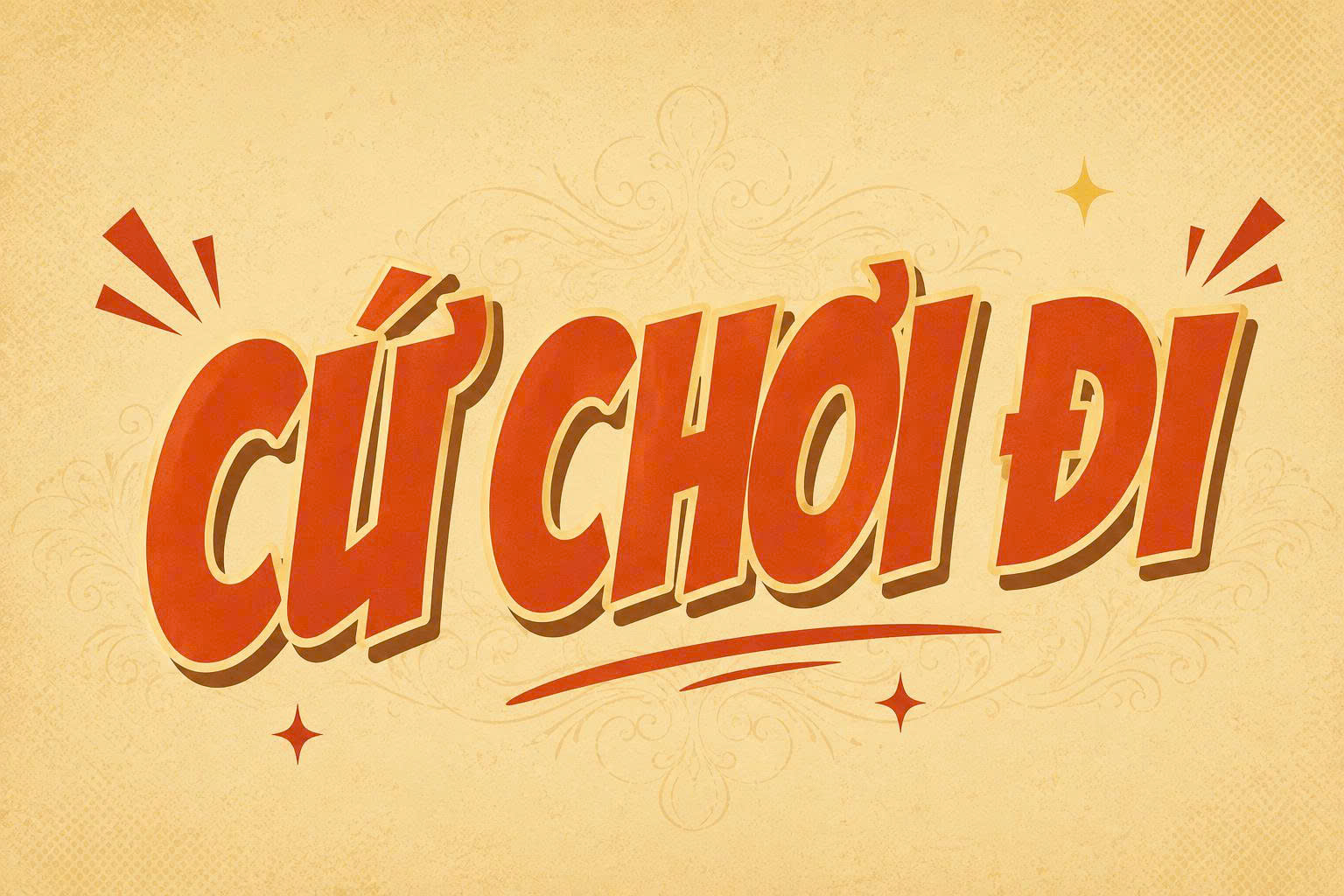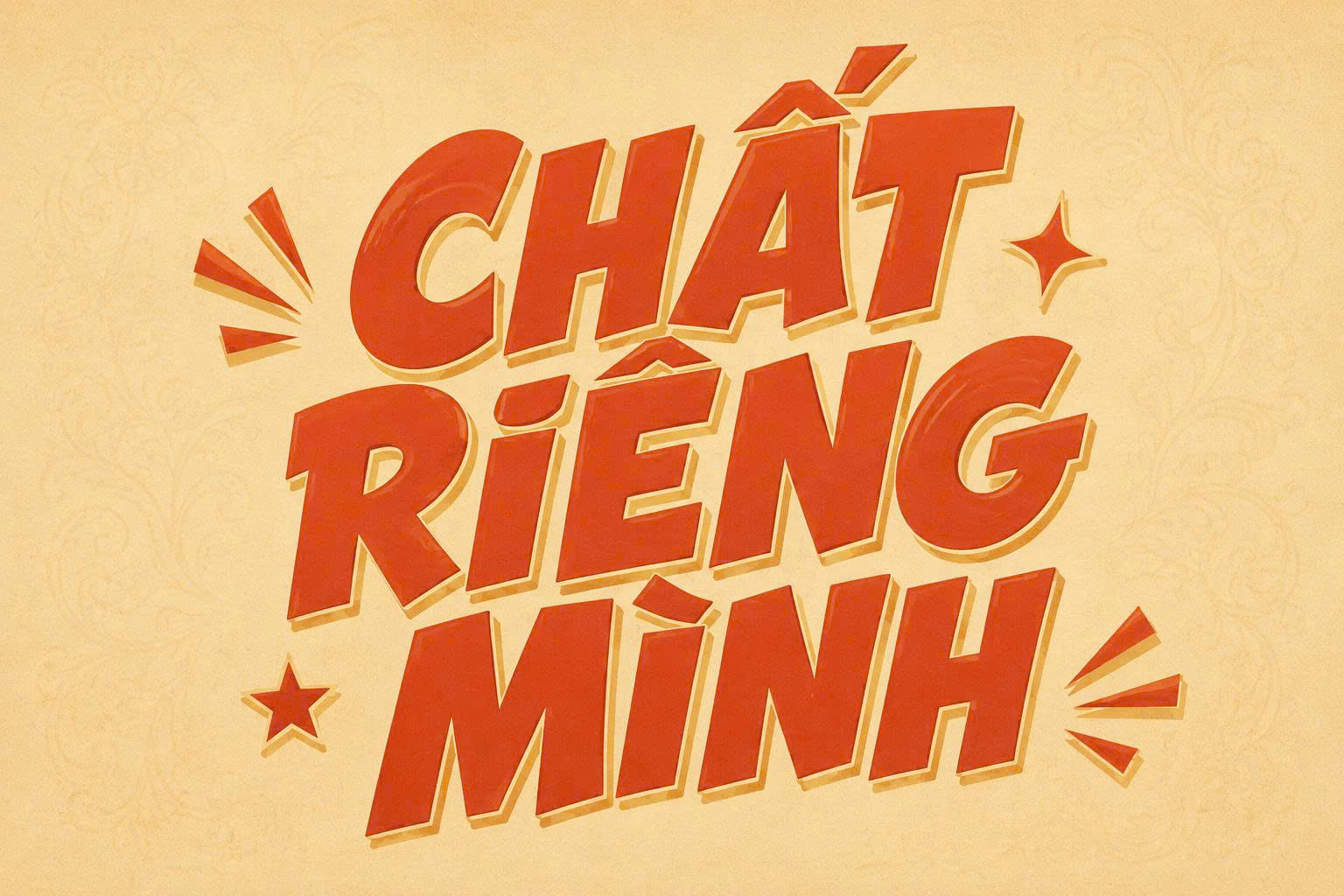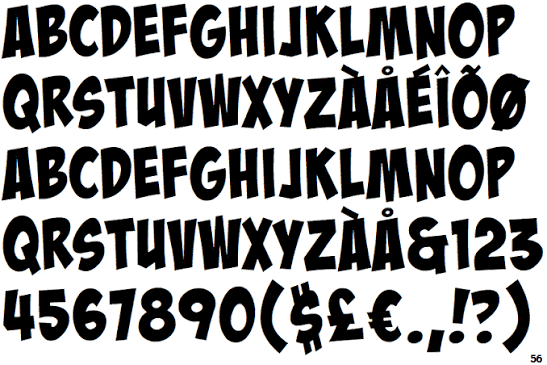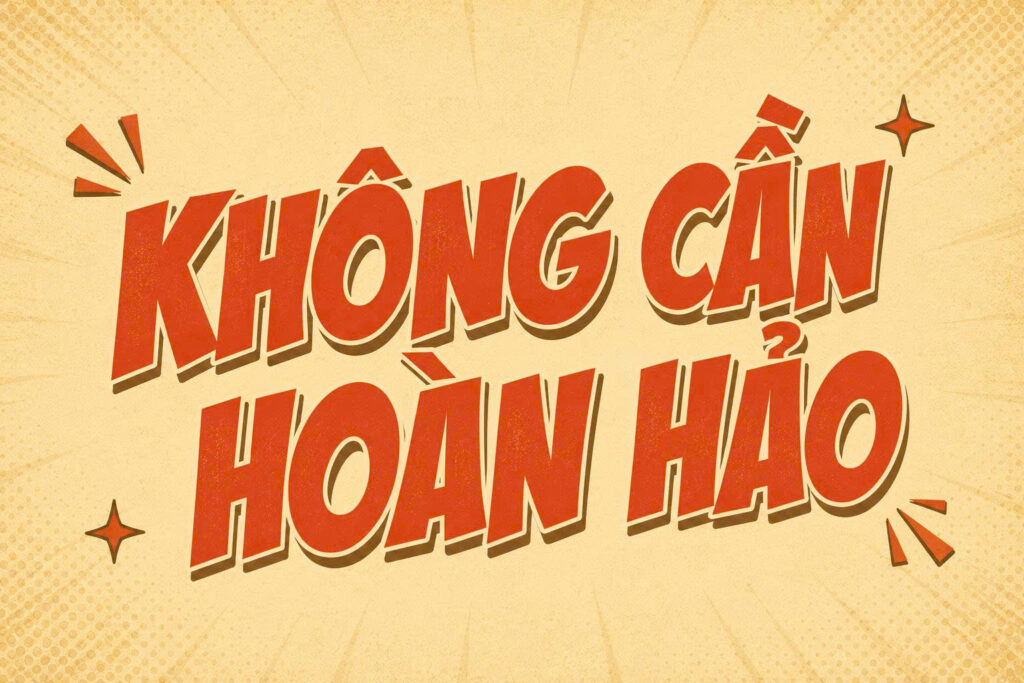
Badaboom font Việt hóa là bộ phông chữ thuộc dòng Comic Display nổi tiếng toàn cầu do Nate Piekos (Blambot) sáng tạo, mô phỏng sinh động các từ ngữ tượng thanh bùng nổ trong các ấn phẩm truyện tranh siêu anh hùng phương Tây. Với các con chữ nghiêng ngả tự do, chân chữ bè to và đường nét đậm đà giàu xung lực, font Badaboom là chất liệu trực quan tuyệt vời để các kiến trúc sư, nhà thiết kế mang lại bầu không khí sôi nổi cho các bản vẽ phối cảnh quán cà phê phong cách comic strip, phòng giải trí board game container hay các khu vui chơi vận động trẻ em.
Nhịp điệu bùng nổ và hiệu ứng âm thanh sống động của Badaboom font Việt hóa
Điểm cuốn hút của Badaboom font Việt hóa nằm ở sự phá vỡ các trật tự dòng kẻ ngang thông thường: các con chữ nhảy múa với độ cao không đồng đều, tạo cảm giác về một tiếng nổ âm thanh vang dội ngay trên mặt bằng thị giác. Cấu trúc chữ sở hữu các góc vát xiên dứt khoát và độ dày nét áp đảo, giúp thông điệp truyền thông đập vào mắt người xem với năng lượng cuồng nhiệt.
Sự ổn định về mặt cảm xúc của dòng font này giúp khuấy động tinh thần lạc quan, xua tan cảm giác nhàm chán và kích thích sự hào hứng cho người sử dụng không gian. Khi kết hợp cùng các vật liệu kiến trúc mang sắc màu Pop Art như vách tôn sóng container sơn màu vàng nghệ, tấm alu đỏ tươi, đèn LED dây rực rỡ hay tranh bích họa khổ lớn, Badaboom tạo nên sự tương thích thẩm mỹ đầy cá tính.
| Phân loại phong cách | Comic Display / Sound Effects / Pop Art Action |
| Mục đích phù hợp | Biển tên khu vui chơi, logo cafe comic, poster sự kiện |
Tư vấn từ chuyên viên: Badaboom sở hữu xung lực thị giác rất lớn và đường nét nén đậm. Để bản thiết kế đạt hiệu quả thẩm mỹ tốt, bạn chỉ nên sử dụng phông chữ này cho các tiêu đề chính, tên thương hiệu hoặc các từ ngữ cảm thán ngắn (như WOW, BOOM, GO).
03 Ứng dụng phông chữ Badaboom vào công trình thực tế
Nhờ vẻ ngoài vui nhộn và tính gợi cảm xúc mãnh liệt, bộ phông chữ này mang lại giá trị thực tế lớn trong khâu tạo điểm nhấn cho các công trình hiện đại:
- Biển hiệu mặt tiền cho Quán Cafe Comic và Phòng Game Container: Những khối chữ nghiêng ngả của Badaboom rất ăn ý khi gia công chữ nổi bằng mica màu vàng viền đen dày gắn trên vách tôn đỏ, mang lại diện mạo bùng nổ, thu hút các bạn trẻ ghé thăm check-in.
- Hệ thống biển chỉ dẫn Khu vận động và Công viên Bạt nhún: Phông chữ này khi in trên các tấm alu phản quang hoặc sơn trực tiếp lên sàn cao su sẽ giúp không gian toát lên chất thể thao đường phố, tạo sự hào hứng cho người tham gia.
- Trang trí không gian sinh hoạt chung Homestay giới trẻ: Bạn có thể dùng font Badaboom để làm tranh bích họa phong cách truyện tranh siêu anh hùng trên tường panel, khơi gợi tinh thần lạc quan và tạo nhiều góc chụp ảnh kỷ niệm ấn tượng cho du khách.
03 Lưu ý bố cục font Badaboom tạo điểm nhấn thị giác ấn tượng
Để khai thác hiệu quả vẻ đẹp của dòng font hiệu ứng âm thanh này mà không gây cảm giác rối rắm cho bản vẽ, người thiết kế nên lưu tâm một số kinh nghiệm sau:
- Bố trí khoảng thở rộng rãi: Do các con chữ có độ nghiêng tự do và chân chữ nở to, bạn nên chừa khoảng trống thoáng đãng xung quanh tiêu đề để khối chữ có không gian bộc lộ năng lượng bùng nổ, tránh bị chèn ép bởi các chi tiết đồ họa phụ trợ.
- Tránh sử dụng cho văn bản dài: Cấu trúc chữ đậm và dáng đứng nhấp nhô của Badaboom không phù hợp cho các đoạn văn bản giải thích chi tiết. Hãy giới hạn trong các cụm từ ngắn từ 1 đến 3 từ để tạo điểm nhấn thị giác tập trung.
- Tận dụng đường viền đậm và Đổ bóng đen: Badaboom phát huy hiệu quả thị giác cao khi phối cùng viền nét đen dày và bóng đổ lệch góc, kết hợp cùng các cặp màu tương phản rực rỡ như vàng – đỏ, xanh dương – cam.